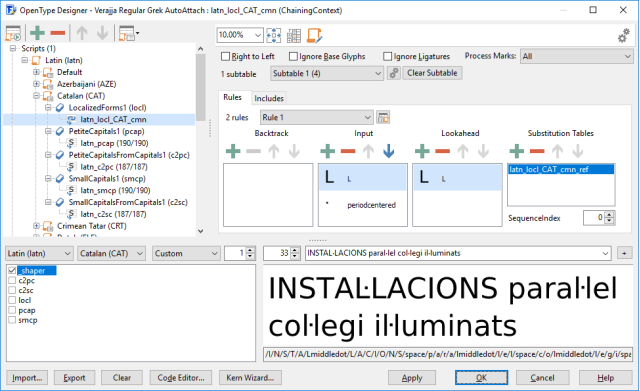
教程 加泰罗尼亚语飞点
No.25 Catalan Punt Volat
本地化形式 - 加泰罗尼亚语飞点
加泰罗尼亚语中存在一些含有两个 L 的词,且这两个 L 各自属于不同的音节,例如 col·legi。在这种场景下,需要在两个 L 之间使用 "punt volat"(飞点)。
在加泰罗尼亚语中,有像 lletres 和 estrella 这样的词使用"双 L",但也有包含两个 L 的词,每个 L 属于单独的音节,例如 col·legi。在这种情况下,在两个 L 之间使用"飞点"(punt volat)。该点应该位于两个 L 的主干之间,最好不在两个 L 之间添加额外的空间。然而,仅输入 L 后跟"居中句点"和另一个 L 将添加"居中句点"的宽度,这不好。
本教程解释如何添加 locl 功能,该功能添加上下文查找,如果后面跟着另一个"L",则将"L periodcentered"替换为 Lmiddledot。
L periodcentered L 设计
为加泰罗尼亚语飞点添加本地化形式功能
您可以使用 FontCreator 轻松地向字体添加本地化形式功能。首先确保您的字体包含所需的字符。
L, l, periodcentered, Lmiddledot, lmiddledot
如果这些字形缺失,您可以通过插入字形对话框添加它们。如果您的字体还包含小型大写字母和/或小型大写字母,请确保它也有这些的变体。
插入字形对话框
接下来,转到 OpenType 设计器并单击左上角的工具栏项。确保选中常用本地化形式选项。
OpenType 设计器 - 常用本地化形式
OpenType 功能和查找现在已添加到您的字体中,如上所示。
您可以输入预览文本来测试您的功能。确保您选择了拉丁脚本和加泰罗尼亚语言并启用了 _shaper 或 locl 功能。您可以输入字母或斜杠后跟字母的字形名称。
INSTAL·LACIONS paral·lel col·legi il·luminats